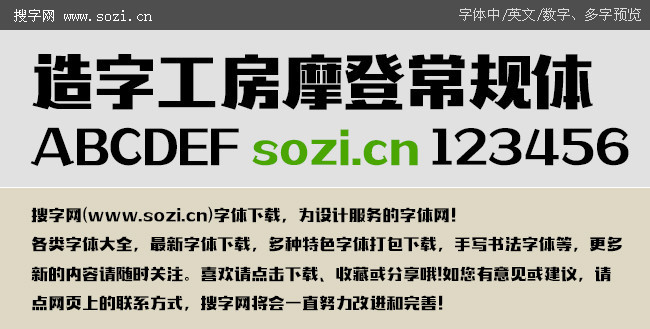
造字工房摩登常規(guī)體
搜字網(wǎng)提供一款造字工房摩登常規(guī)體中文藝術(shù)字體下載,造字工房摩登常規(guī)體字體個(gè)性鮮明,,該字體線條粗壯有力,字形端正大方得體,整體效果非常出色,且字庫完整。此款字體適用于兒童讀物、報(bào)刊雜志標(biāo)題、廣告設(shè)計(jì)等領(lǐng)域。